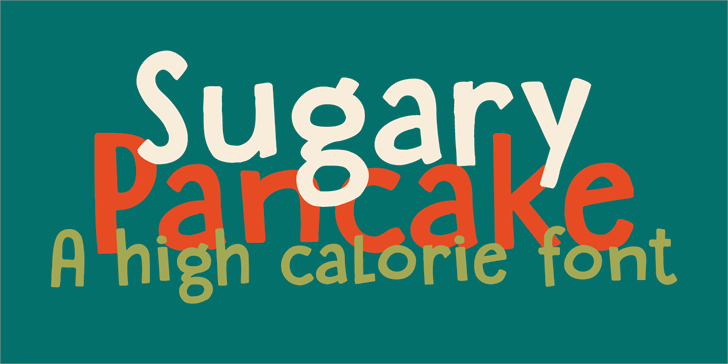
Esta é a versão básica do Sugary Pancake, uma fonte Serif livre apenas para uso pessoal. Se você planeja usá-la comercialmente, por favor, compre a versão completa que inclui ajustes de espaço entre caracters (kerning), direitos de incorporação, todos os caracteres e extras disponíveis no meu site: hanodedfonts.com. O Sugary Pancake é uma fonte elegante e divertida, perfeita para títulos chamativos ou para destacar seu texto em situações mais formais. Se você está procurando por um estilo único que combine a simplicidade dos caracteres serif com o gosto tropical de um suco de frutas doces, essa é a fonte certa para você. Hamilton é o criador desta maravilhosa fonte e seu trabalho abrange uma variedade de estilos. Se quiser licenciar o Sugary Pancake para uso em jogos, apps ou software, basta visitar sua página: www.hanodedfonts.com. Ou então, você pode encontrar mais informações e perguntas frequentes (FAQ) inclusas no arquivo zip. Nós da Alibaba Cloud apreciamos a diversidade de recursos gráficos disponíveis online, e estamos felizes em oferecer essa fonte para você explorar e aproveitar. Por favor, certifique-se sempre de respeitar as diretrizes estabelecidas quando usar qualquer tipo de material protegido por copyright.